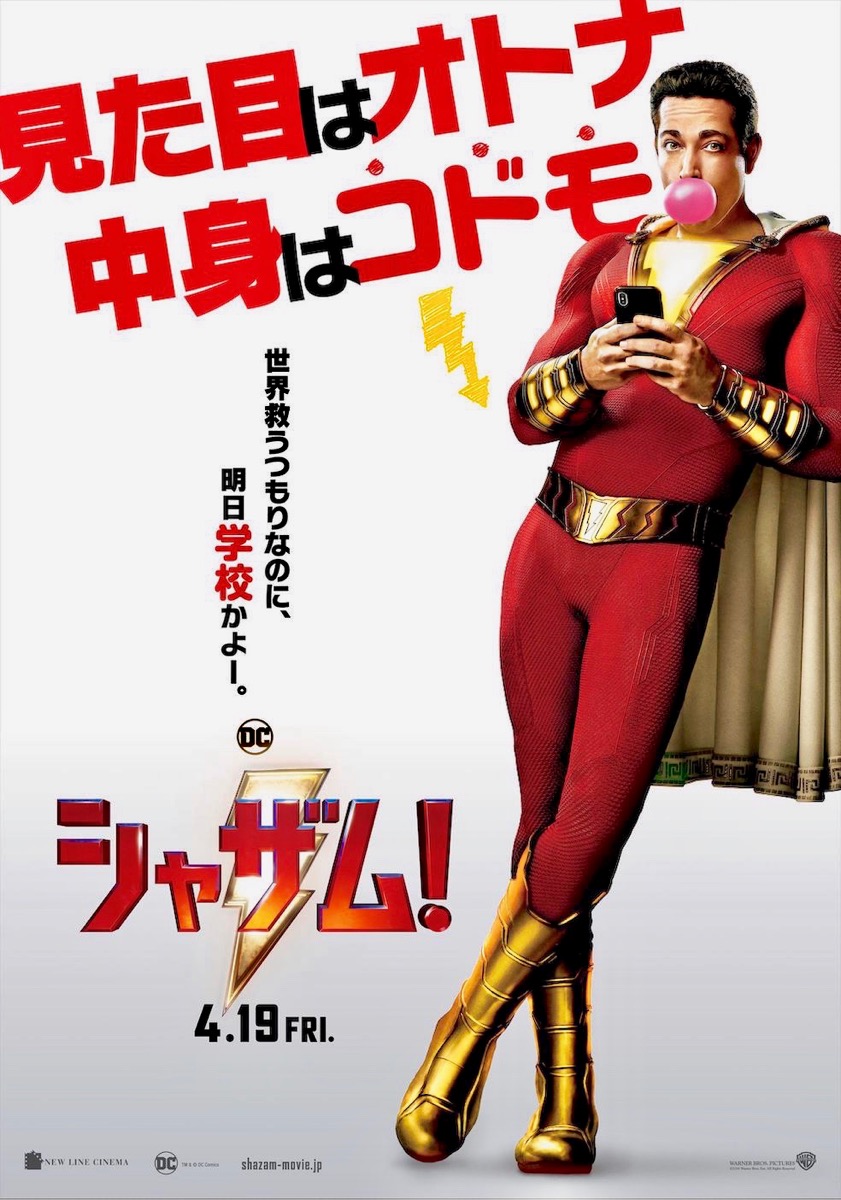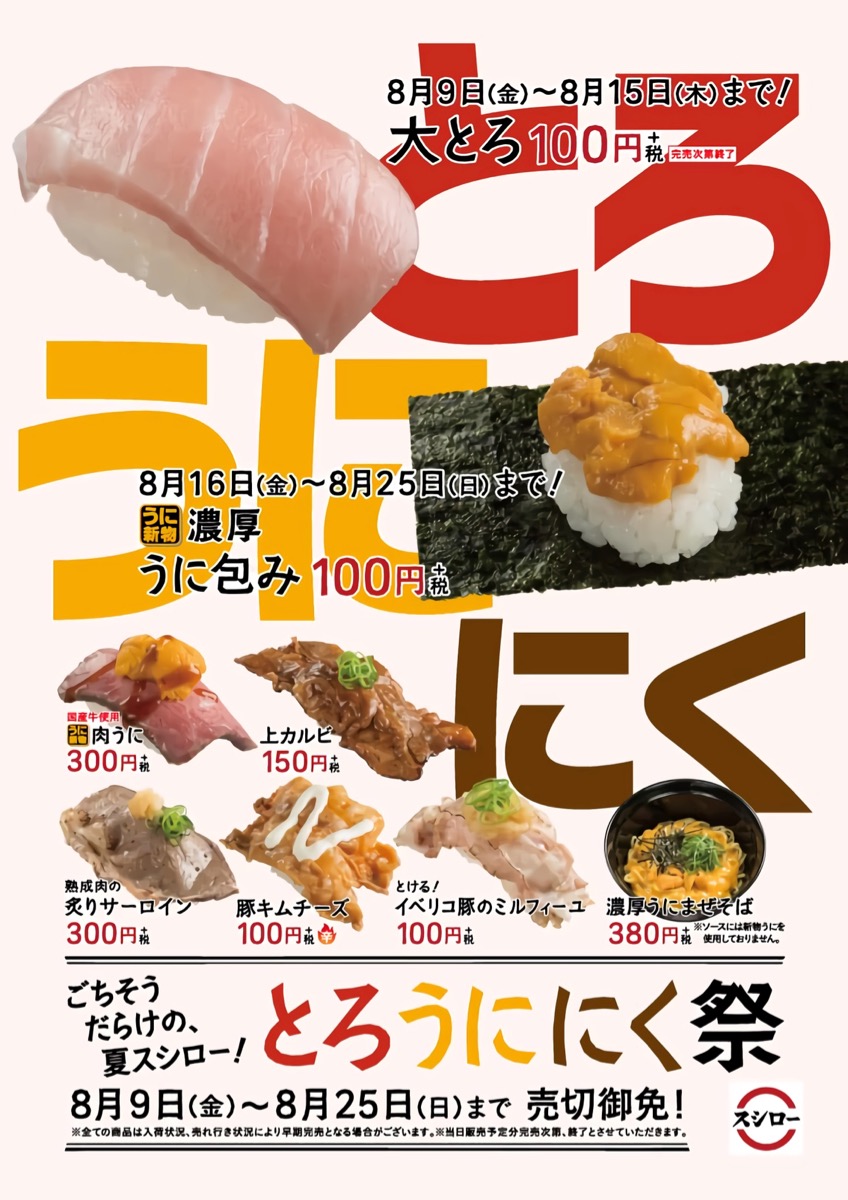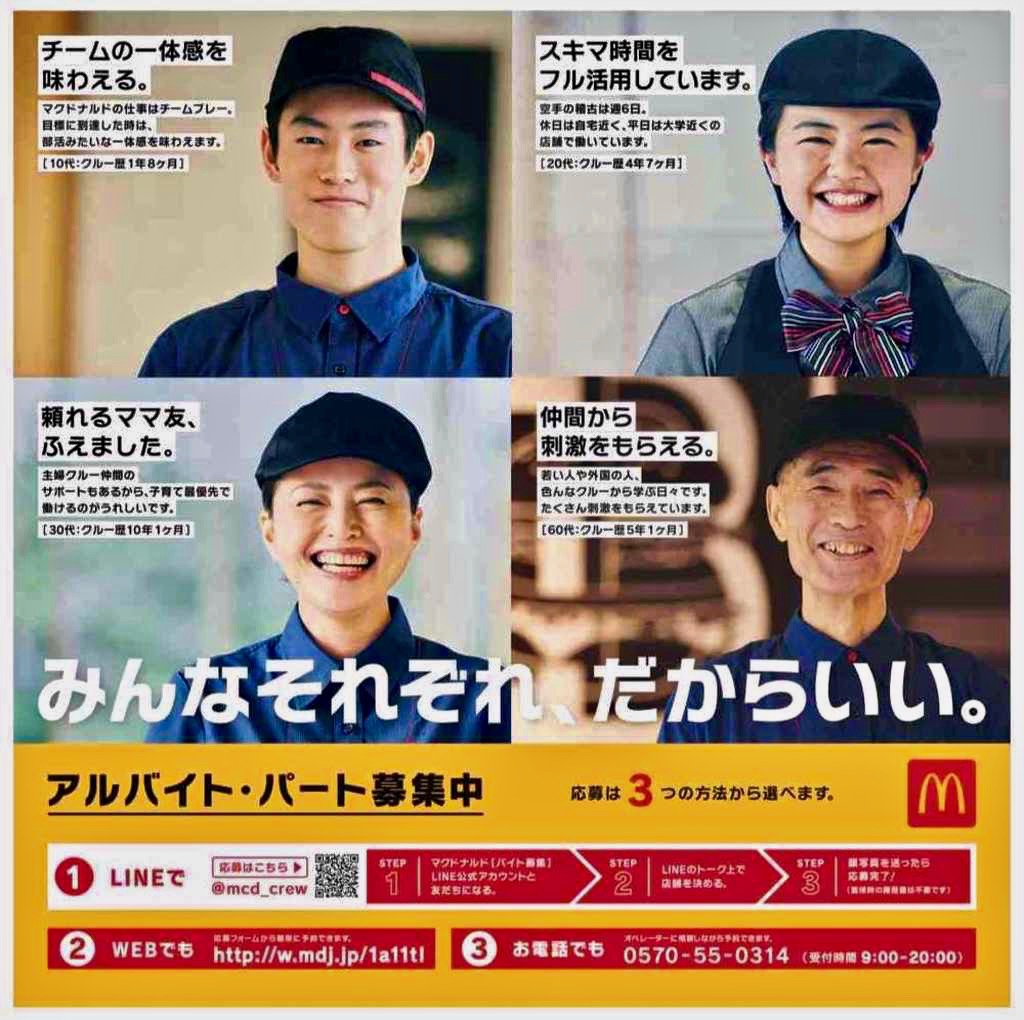
サイゼリヤ  さとうゆたか  2020年6月6日(土) 16:02
ここもお持ち帰りできるようになった…。
こちらは、WEBサイトの画像。
マクドナルド  さとうゆたか  2020年5月30日(土) 16:17
「タッタ」ではなく「タツタ(竜田)」だということに、最近気づいた。
商品ロゴ  さとうゆたか  2020年5月24日(日) 16:01
お風呂掃除用の洗剤名ロゴ。
テレビ番組  さとうゆたか  2020年5月15日(金) 11:20
日本テレビ「有吉の壁」だったかな。
これも…。
テレビCM  さとうゆたか  2020年5月3日(日) 15:27
マクドナルド。
これも…。
ガンガンコミックスONLINEの告知動画  takumi  2020年4月28日(火) 16:47  HP
スクウェア・エニックス公式チャンネルにアップされている、ガンガンコミックスONLINEの告知動画で「ニタラゴルイカ」が使われているようです。
おそらく、最も太い09ウェイトで、商品版のようです。
↓これは、「4月の新刊」告知動画。
参考に、もう1枚。
ニタラゴルイカ商品版、使用例を見つけるのは大変ですよね(笑)。
テレビ番組  さとうゆたか  2020年4月27日(月) 14:59
フジテレビの「めざましどようび」。
これは土曜日の番組だが、平日の「めざましてれび」にも同様に使われている。
これも追加。
もうひとつ…。
キャンペーンロゴ  さとうゆたか  2020年4月18日(土) 15:51
キューピーのテレビCM。
リニューアルした「ケンミンSHOW」  takumi  2020年4月18日(土) 5:10  HP
4月から大幅リニューアルした「秘密のケンミンSHOW 極(きわみ)」(日テレ系)でニタラゴ書体が使われています。
F社にライセンスされているもののようですね。
最後にもう1枚。
いちばん太いニタラゴをメインに、画面の上の文字とか、もう少し細いウェイトも含めて幅広く使ってくれているみたいです。
この番組、いつも見てます。
パイセン  さとうゆたか  2020年4月9日(木) 9:43
期間限定商品らしい。
ベーコンポテトパイセン。
これも…。
商品パッケージにも。
もうひとつ。